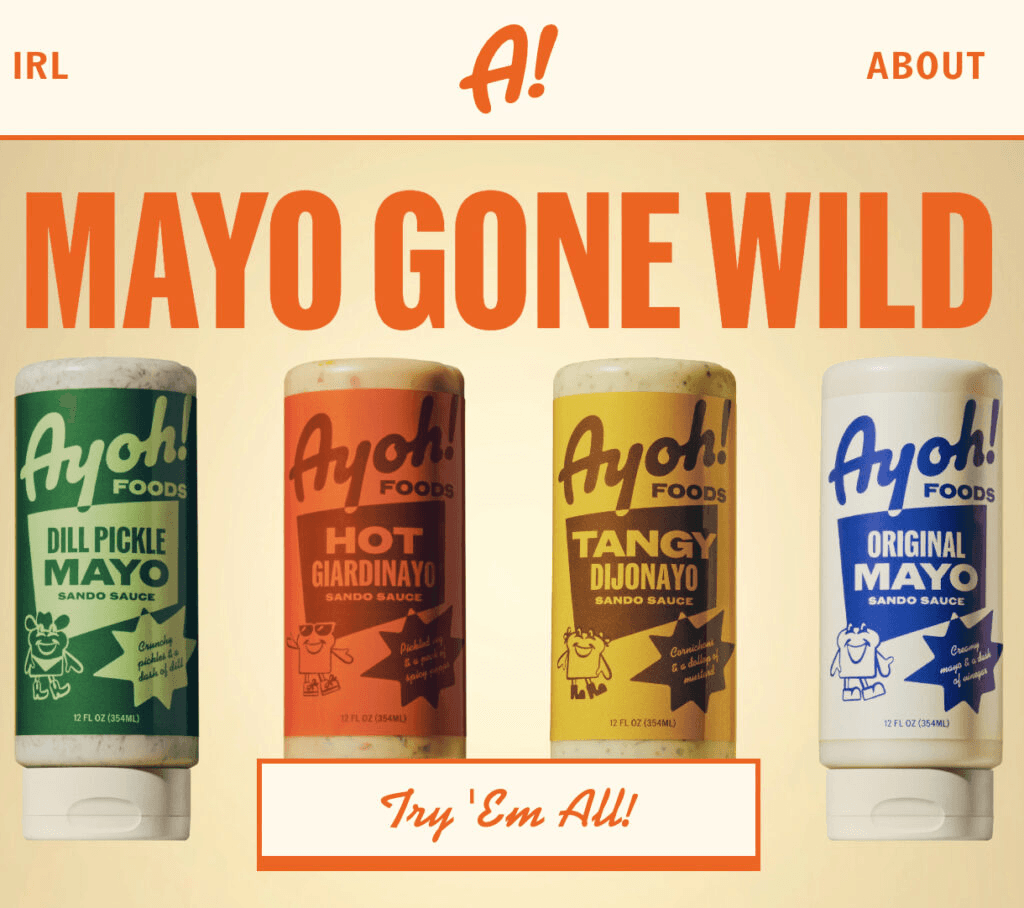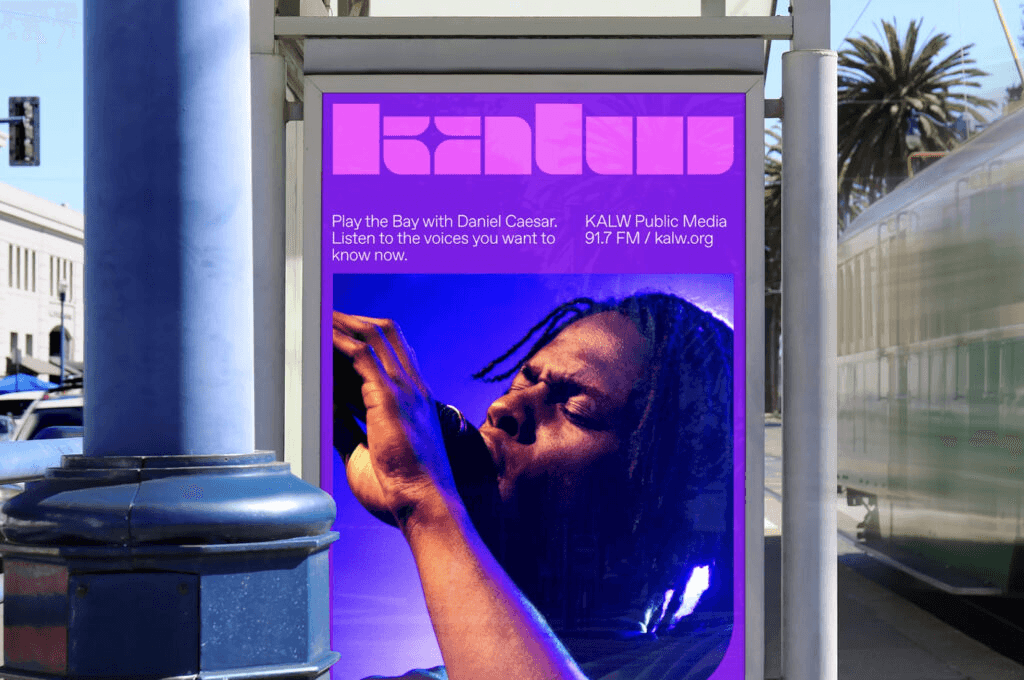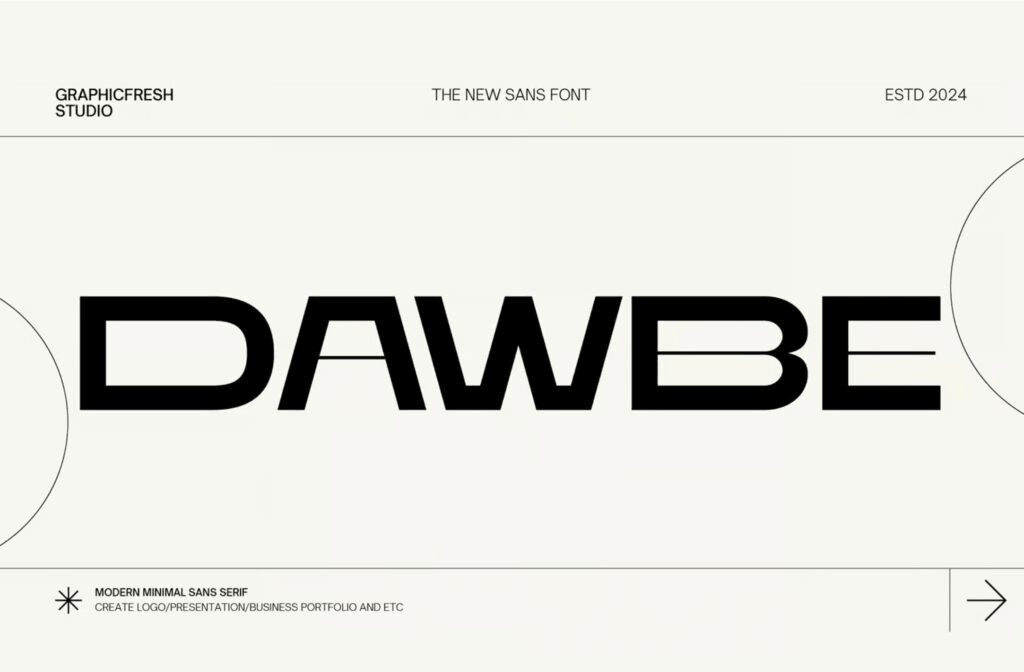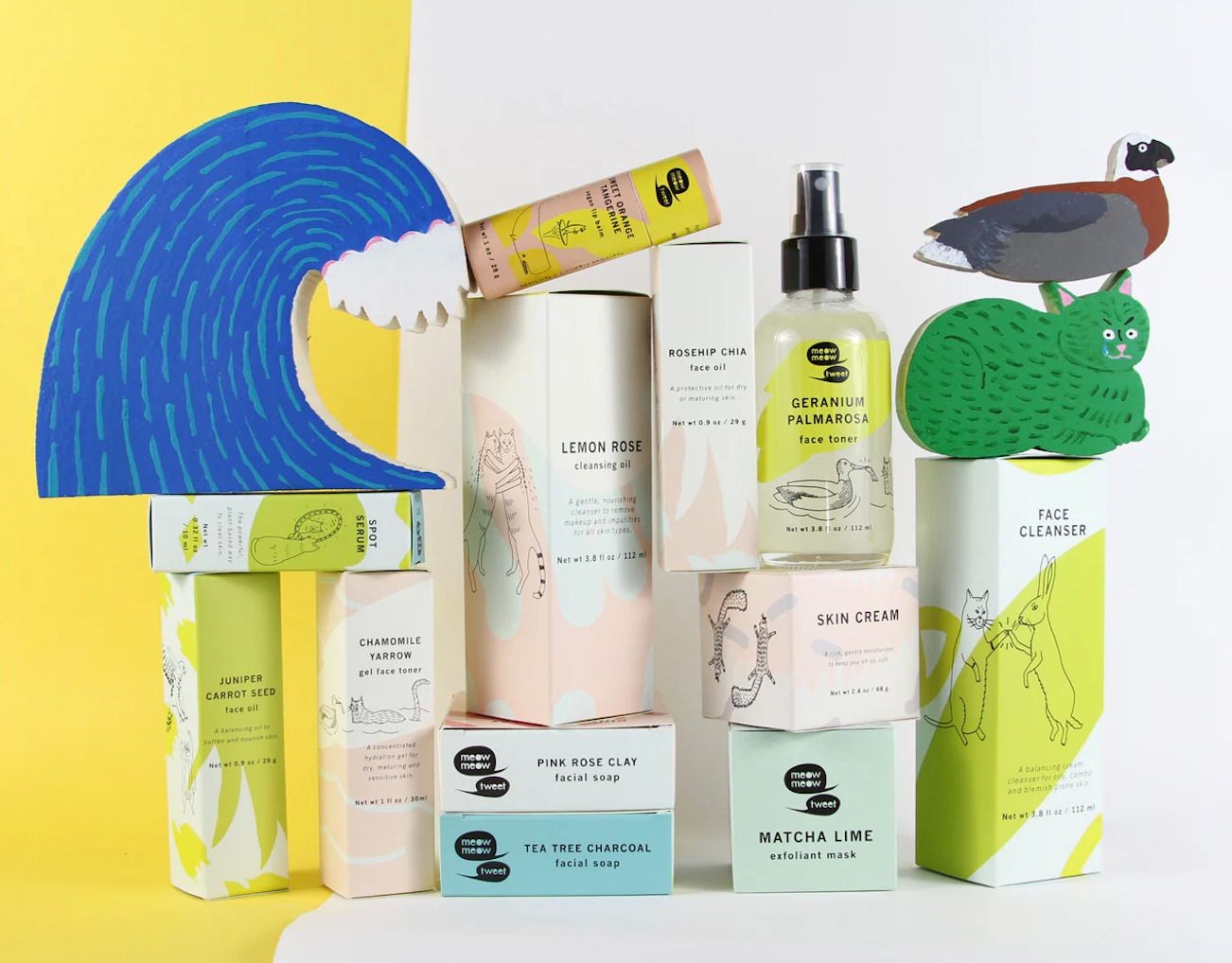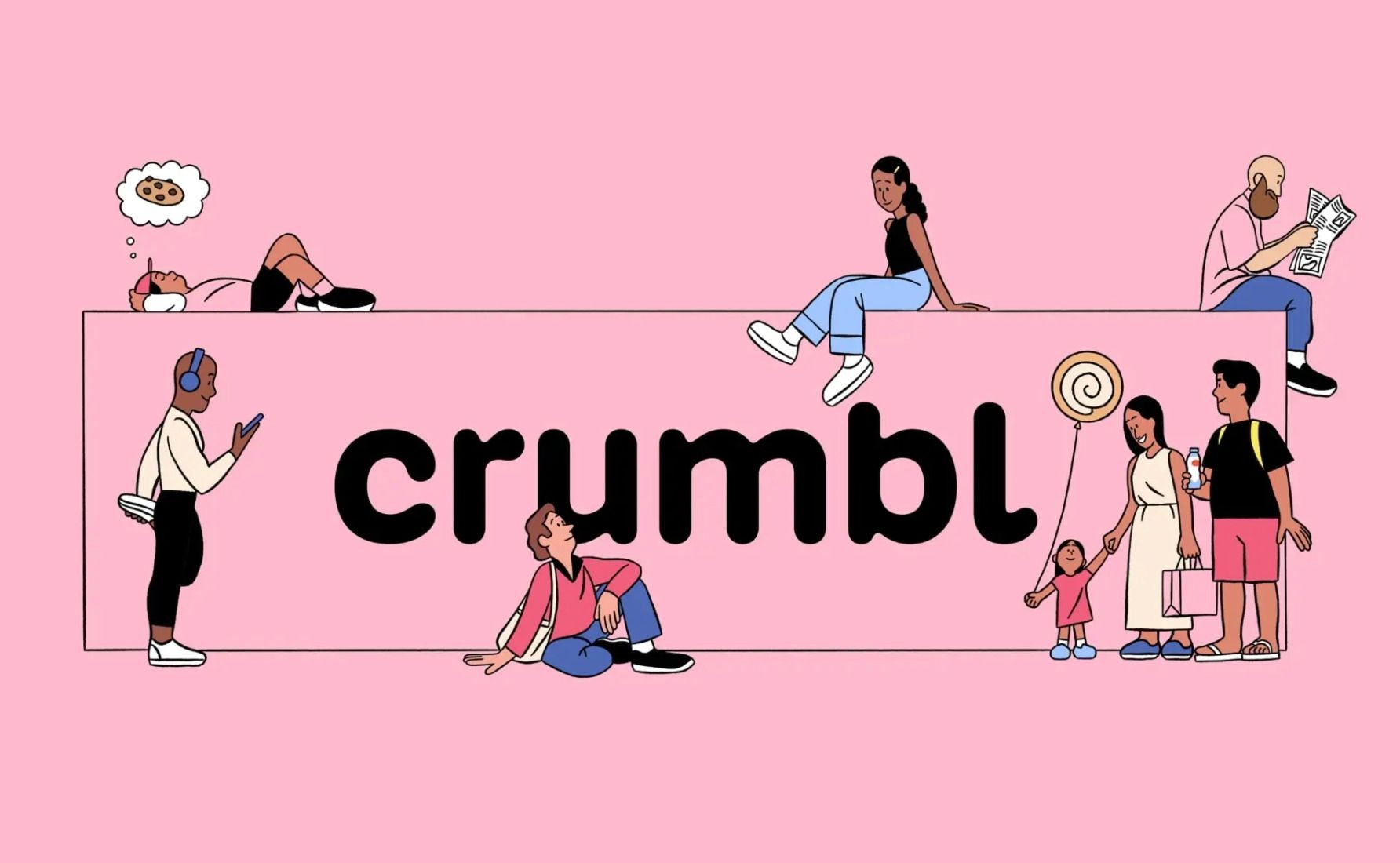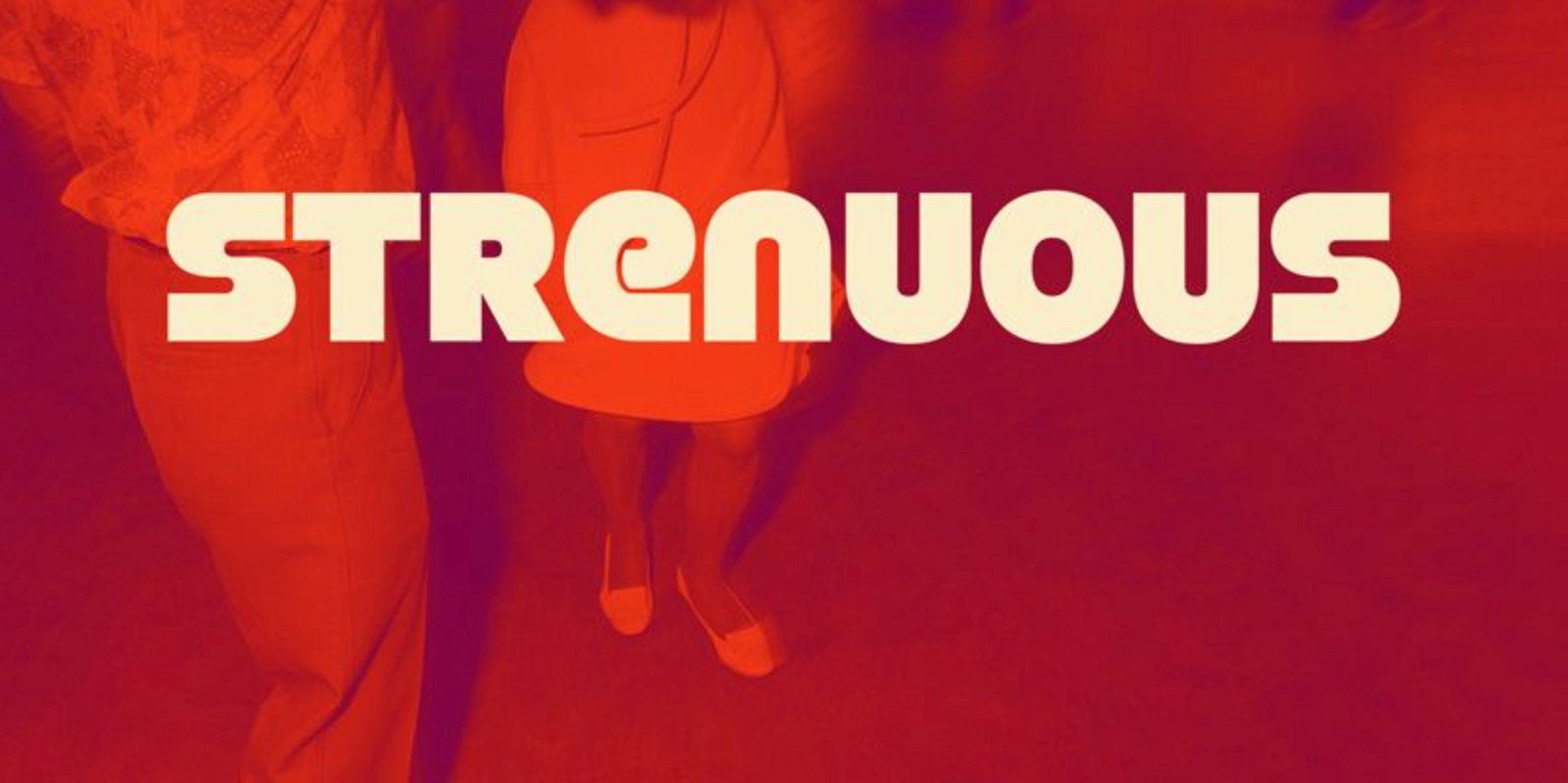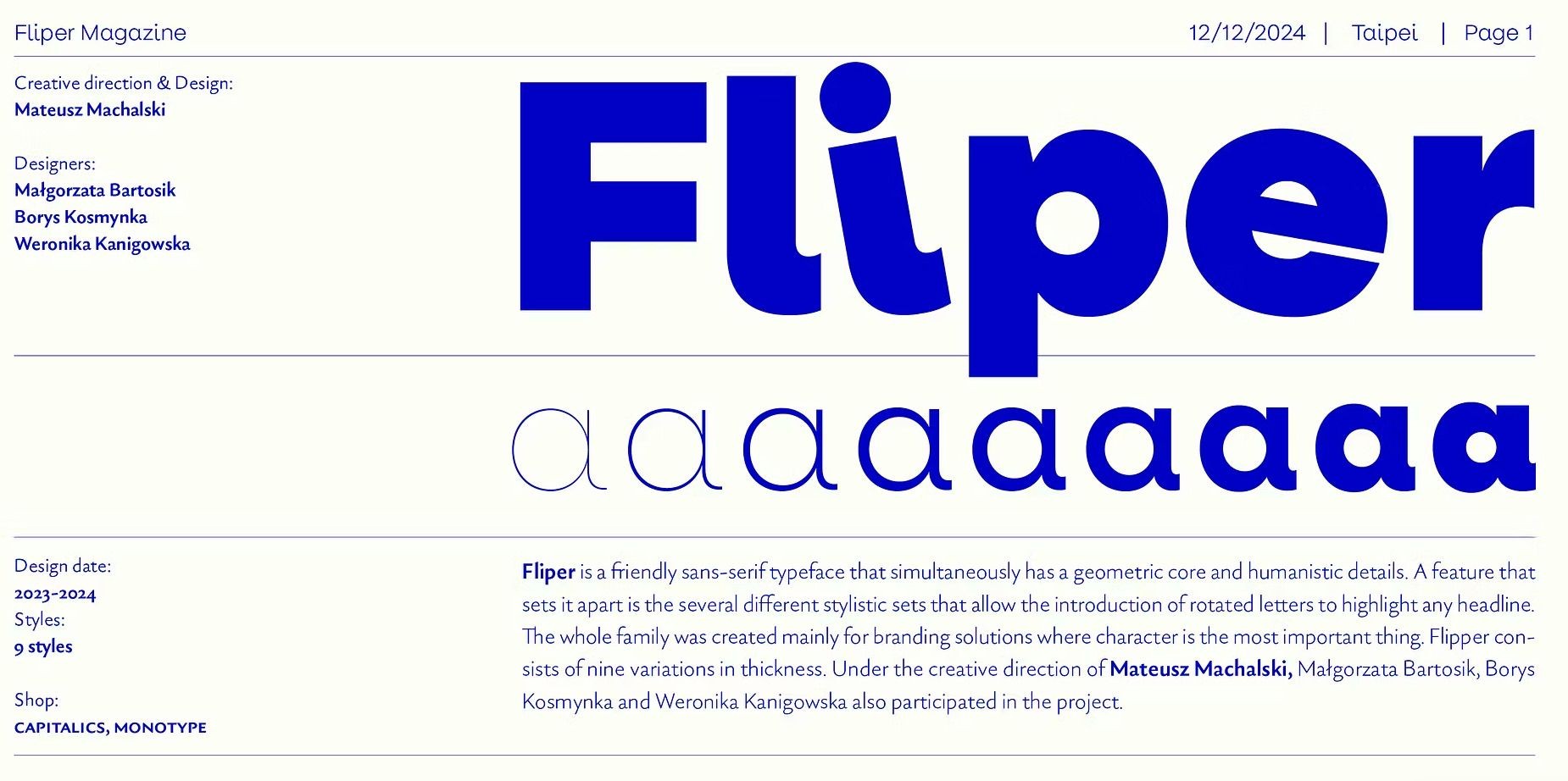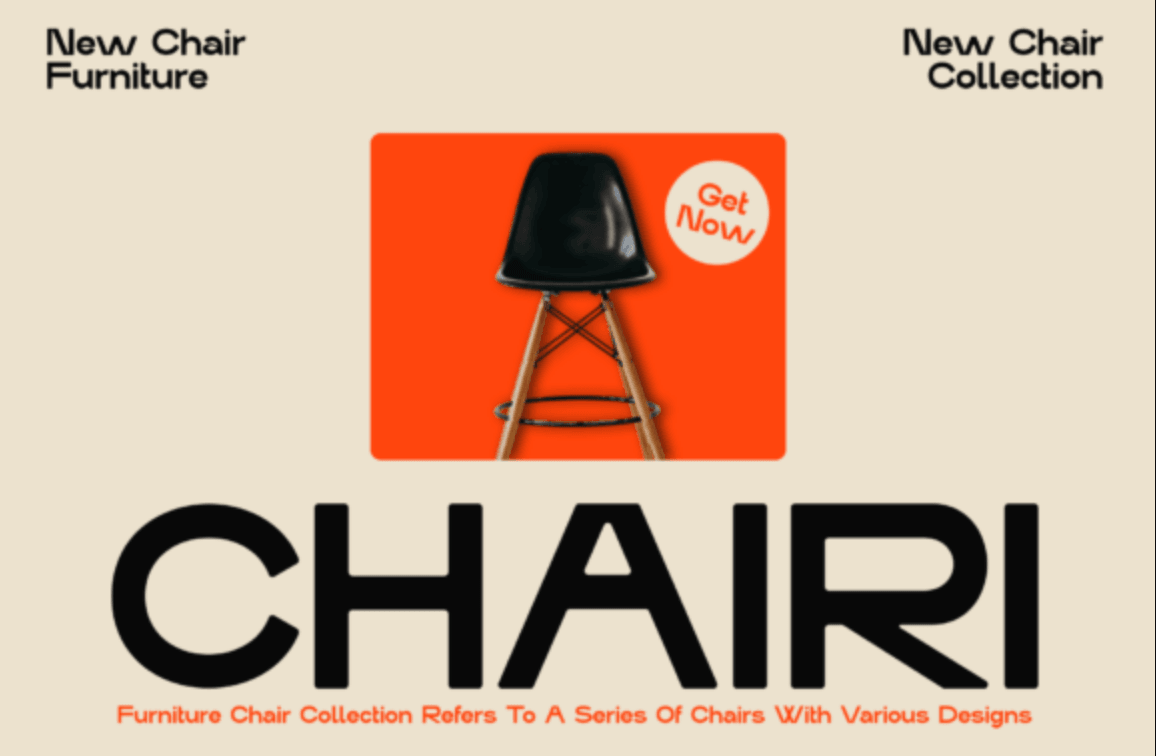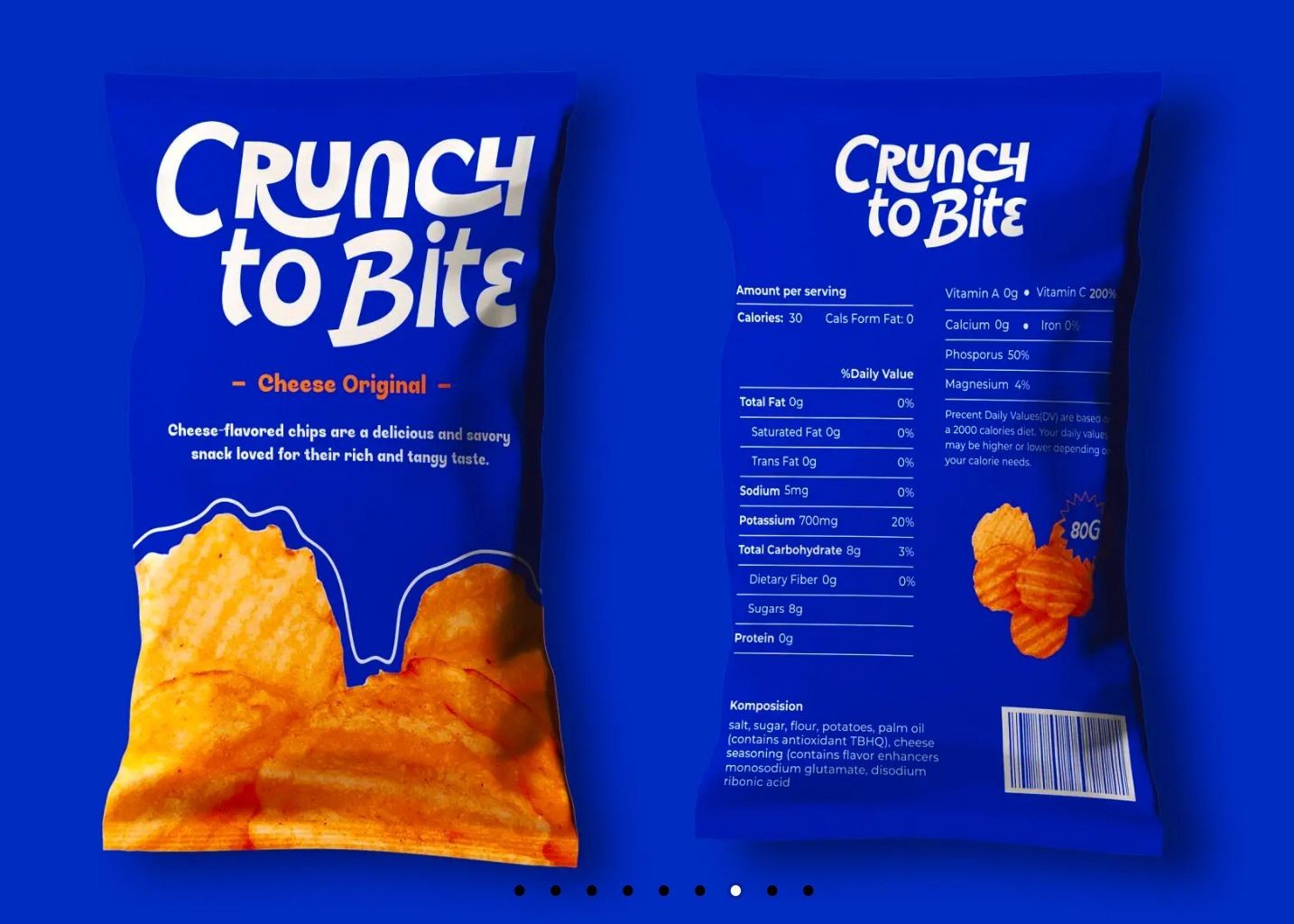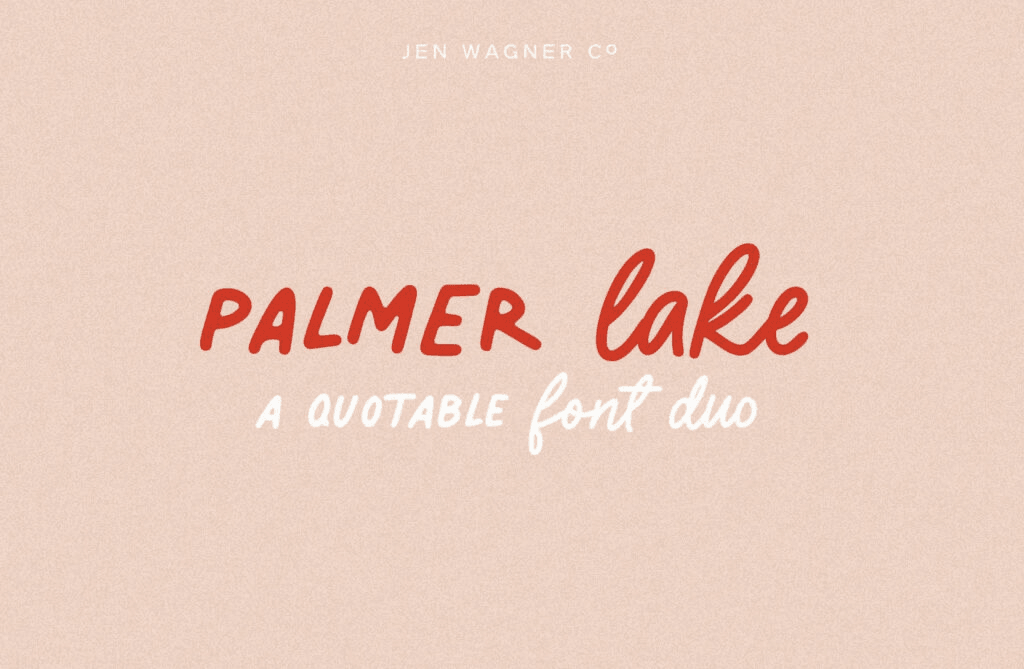
2025년 폰트 트렌드: 인간적, 미래적, 굵은 글꼴
감성적인 손글씨부터 미래지향적 디스플레이까지,
개성과 진정성을 담은 대담한 폰트가 주류!
2025년 기업가와 디자이너들 사이에서 가장 많이 선택되는 로고 글꼴 에 대한 로고 제작자 데이터를 살펴보았습니다. 맞춤 제작된 손글씨체, 붓놀림, 그리고 대담한 블록형 디스플레이 폰트이 등장했습니다. 또한, 추상적이고 미래지향적인 폰트도 등장했습니다! 이러한 트렌드는 인간과의 연결과 기계의 발전에 대한 열망을 보여줍니다.
우리는 2025년 주목할 만한 5가지 폰트 트렌드를 분석하고, 주요 디자인 매체와 인기 폰트 사이트를 조사해 올해 트렌드를 잘 보여주는 대표 폰트 20가지를 엄선했습니다. 다음과 같습니다.
트렌드 #1: 사랑을 담아 손으로 쓴 글
손으로 쓴 글꼴은 2025년에 인기가 급증했는데, 이는 디지털 중심의 세상에서 진정성과 개인적 연결에 대한 열망을 보여줍니다.
디자이너와 기업가들은 더욱 친근하고 인간적이며 독특한 디자인을 선호하고 있습니다. 손글씨 폰트는 브랜드 아이덴티티 에 따뜻함과 개성을 더합니다 . 또한 정성이 담긴 느낌을 중시하는 사람들에게도 매력적입니다! 요즘 우리 대부분은 손글씨 폰트에 푹 빠져 있죠.
이러한 글꼴의 불완전함은 개성을 표현하여 세련되고 현대적인 시장에서 브랜드가 더욱 공감대를 형성하도록 돕습니다. 이러한 추세는 디자인과 메시지 전달 모두에서 진정성 있고 진심 어린 소통에 대한 수요가 증가하고 있음을 보여줍니다. 사람들은 브랜드와 연결되고 싶어 합니다!
이러한 트렌드는 의류, 스킨케어, 식음료, 향수처럼 감성적인 무드와 브랜드 스토리가 중요한 분양에서 특히 인기가 높습니다.
Popup Bagels는 맛있는 수제 베이글과 그에 어울리는 손글씨 로고 폰트로 뉴욕을 강타했습니다.
Dedcool은 독창적인 향과 무독성 유기농 성분으로 향수 시장에 신선한 반향을 일으키고 있어요. 손으로 직접 쓴 듯한 유니크한 폰트는 브랜드의 개성을 더욱 강렬하게 표현해줍니다.
디지털 의류 및 액세서리 매장도 손글씨 폰트의 독특한 느낌을 연출하기에 완벽한 장소입니다.
손으로 쓴 글씨체에 대한 몇 가지 아이디어를 소개합니다.
1. Palmer Lake
출처: Jen Wagner Co의 Palmer Lake 폰트
2. Biro Script
3. Prosecco and Baguette
4. Shantell Sans
트렌드 #2: 브러시를 활용하세요
올해는 붓놀림의 빠르고 역동적인 움직임이 유행입니다. 브러시 글꼴은 대담하고 표현력이 풍부한 개성을 지닙니다. 이러한 글꼴은 보통 손의 움직임을 표현하기 위해 앞으로 기울어져 있습니다. 빠른 서명이나 빠르게 움직이는 브랜드의 마크처럼 말이죠.
이러한 글꼴은 가독성과 시그니처 같은 디자인으로 개인 브랜딩 에 널리 사용됩니다 . 또한 뷰티, 식음료 산업, 그리고 고전적인 무드와 현대적인 감성을 함께 담아내는 브랜드에도 제격이에요.
브러시 글꼴은 다양한 스타일을 가지고 있습니다. 거친 질감이 있는 스타일이든, 굵고 세련된 글씨체든, 브러시 글꼴은 다양한 스타일과 활용법을 가지고 있습니다. 몇 가지 예를 들어 보겠습니다.
The Unwash 로고의 대담하고 복고풍 느낌은 역동적이며, 모던함과 빈티지 스타일의 균형을 이루고 있습니다.
Mindful Chef는 마커로 쓴 듯한 브러시 필기체를 활용해, 따뜻하면서도 믿음직한 브랜드 이미지를 완성했어요.
Bubs and Grandma의 브랜딩은 장인 정신을 담아 의도적인 결점을 살린 독특한 디지털 브러시 룩을 선보입니다. Ayoh의 로고 폰트는 굵은 획과 곡선형 끝이 특징인 역동적인 디지털 브러시 폰트로, 따뜻하고 친근한 느낌을 줍니다. 기울어진 형태는 강조되면서, 강렬해 보이게 합니다.
이런 트렌드에 맞춰 사용할 수 있는 몇 가지 글꼴을 소개합니다.
5. FS Sammy
6. Goodlife
7. Mercato
8. Duos
트렌드 #3: 대담한 디스플레이
대문자와 볼드체의 강렬하고 위풍당당한 존재감이 올해 주요 글꼴 트렌드로 자리 잡았습니다. 볼드체ㄴ,ㄴ 자신감과 권위를 부여합니다. 대문자로 된 단어 하나가 소문자로 된 문장 전체보다 더 많은 관심을 끌기 때문입니다.
이러한 트렌드는 타이포그래피 스타일 과 좋은 카피가 중심이 되는 기능적 디자인을 지향하는 전반적인 추세와 일맥상통합니다. 올해 그래픽 디자인 트렌드라고 할 수 있죠!
볼드체의 증가는 깔끔하고 당당한 시각적 표현으로의 전환을 반영합니다. 디자이너들은 강렬하면서도 간결한 디자인을 추구하고 있습니다. 굵은 글꼴은 다양한 스타일로 활용될 수 있습니다. 다양한 환경과 용도에 활용되는 굵은 글꼴의 몇 가지 예를 소개합니다.
Collins의 Andmore 브랜딩
Superfried Agency의 머스타드 브랜딩
Collins의 Kalw 브랜딩
시작하는 데 도움이 되는 몇 가지 글꼴 아이디어는 다음과 같습니다.
9. Armada
10. Sazerak
11. Surge
12. Lock Block
기술은 끊임없이 변화하는 세상의 주요 원동력입니다. 아직 하늘을 나는 자동차는 없지만, 미래를 만들어갈 멋진 신기술에 기대지 않을 수 없습니다. 이러한 열망은 브랜딩과 디자인 분야에서 미래지향적인 글꼴 선택으로 나타나고 있습니다.
이러한 폰트은 혁신, 진보, 그리고 기술 발전을 상징합니다. 따라서 이러한 콘셉트에 부합하는 브랜드나 디자이너에게 적합합니다. 세련된 기하학적 로고 형태와 개성 있는 글자 조합, 그리고 전반적으로 간결한 디자인이 특징입니다.
게임 , 기술 스타트업, 디지털 제품, SF에서 영감을 받은 콘셉트 등 다양한 산업에 적합합니다 . 디자인 분야에서 볼 수 있었던 독특한 미래지향적 글꼴 몇 가지를 소개합니다.
Collins의 자유형 브랜딩
Superfried의 Revere 브랜딩
Ragged Edge의 No Two Ways 브랜딩
이러한 트렌드를 포착하는 데 도움이 되는 몇 가지 글꼴을 소개합니다.
13. TT Paplane
14. Teknolog
15. Golgix
16. Dawbe
트렌드 #5: 불완전한 산세리프
이 글꼴 트렌드는 첫 번째 트렌드인 손글씨체와 산세리프체의 깔끔한 디자인이 조화를 이룬 것입니다 . 산세리프체의 깔끔한 가독성과 손글씨체의 재치 있는 디자인을 모두 갖추고자 하는 바람에서 탄생한 이 트렌드는 눈에 띄면서도 확고한 정체성을 유지하는 데 중점을 두고 있습니다.
개성과 모던한 감각을 모두 담고 싶은 이들을 위해, 기본 산세리프에서 발전한 다양한 서체 스타일이 주목받고 있습니다. 부드러운 곡선, 원형 디테일, 글자 연결, 그리고 길쭉한 비율 등이 대표적인 특징입니다. 이 서체들은 각자의 방식으로 자신만의 색깔을 표현하고 싶어 하는 사용자들에게 매력적으로 다가갑니다.
이 트랜드는 가장 다재다능한 폰 중 하나로, 어떤 산업에도 적합하며 디자이너들이 원하는 방향으로 자유롭게 작업할 수 있도록 해줍니다. 몇 가지 예시를 소개합니다.
다음의 독특하고 불완전한 산세리프체에 이러한 트렌드를 적용해 보세요.
17. Strenuous
18. Flipper
19. Minati
20. Lacotte
글꼴 트렌드의 중요성
디자이너, 기업가, 그리고 창의적인 사람들로서 우리는 끊임없이 영감과 새로운 아이디어를 찾아 나섭니다. 똑같은 디자인과 글꼴을 사용하는 것은 지루하고 누구에게도 감동이나 공감을 주지 못합니다. 진화는 우리 DNA의 일부입니다.